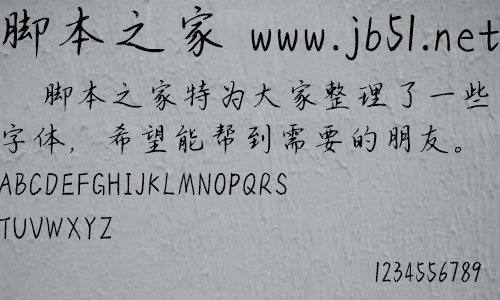
漢儀人性不可試簡(jiǎn)一款不錯(cuò)的藝術(shù)字體,由漢儀字庫(kù)出品,字體筆觸適中,字形圓潤(rùn),具有很好的視覺(jué)感,適合應(yīng)用于藝術(shù)設(shè)計(jì)、平面宣傳設(shè)計(jì)、網(wǎng)頁(yè)設(shè)計(jì),書(shū)法字帖等領(lǐng)域,需要的朋友可以前來(lái)本站下載。